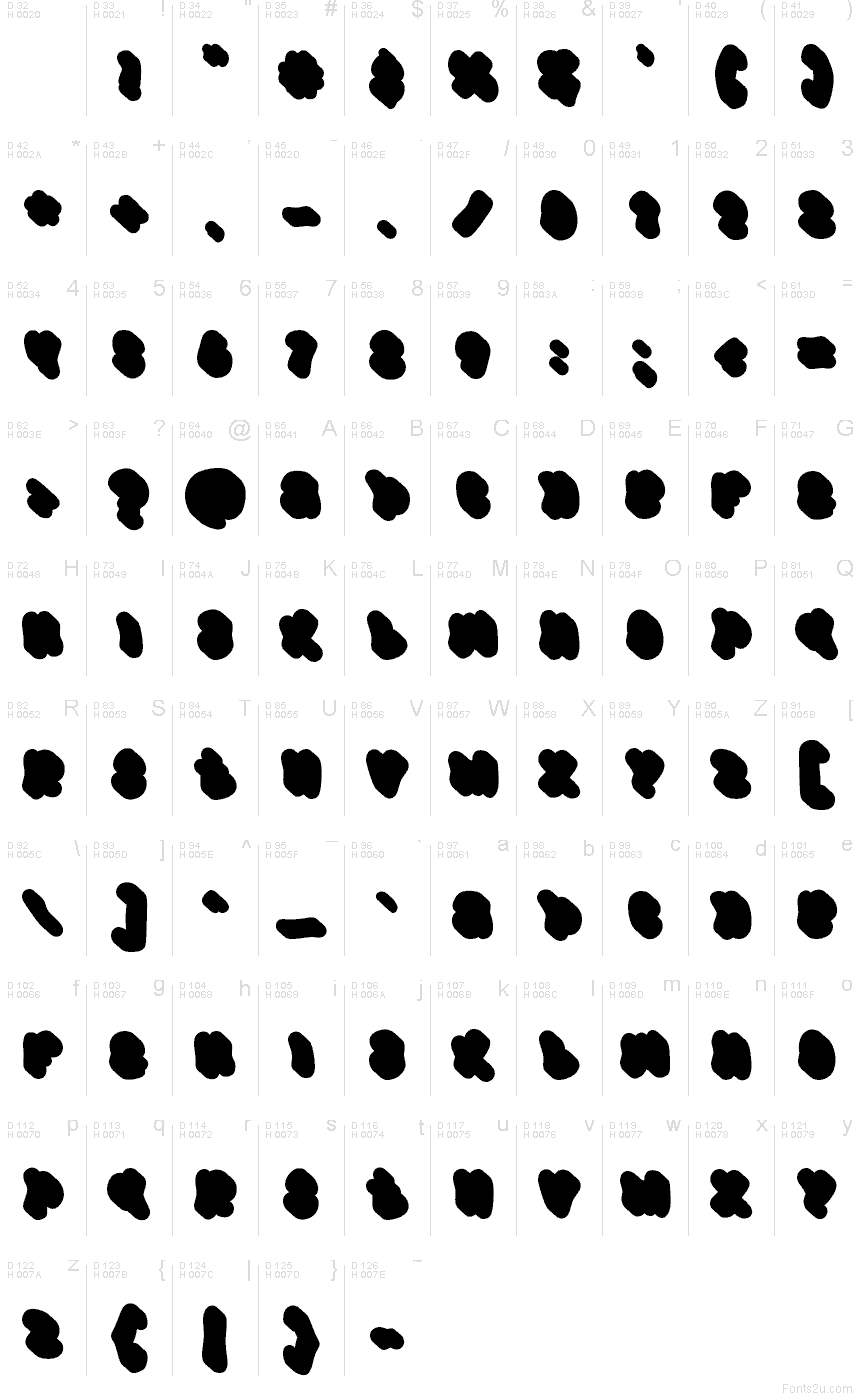
Onyx Vibe Extrude di Muhammad Panji Ramdhani di Sipanji x Figuree è un font graffiti gratuito, spesso e corposo, caratterizzato da tratti gonfi simili a nuvole che si accumulano in una silhouette audace ed estrusa. Sembra vernice spray fresca: bordi morbidi, spaziatura stretta e un ritmo pesante che trasforma ogni parola in un tag d'impatto che puoi quasi sentire al tatto.
Con Onyx Vibe Extrude darai un carattere deciso a grafiche streetwear, copertine di album, poster di skate, overlay per Twitch, pacchetti di adesivi, volantini per eventi e titoli social d'impatto. Usalo in grande formato per lasciar respirare le sue forme dense e abbinalo a un sans serif pulito e condensato per date, didascalie o dettagli di merchandising: questo font gratuito si occuperà di farsi notare, mentre il resto manterrà la massima leggibilità.